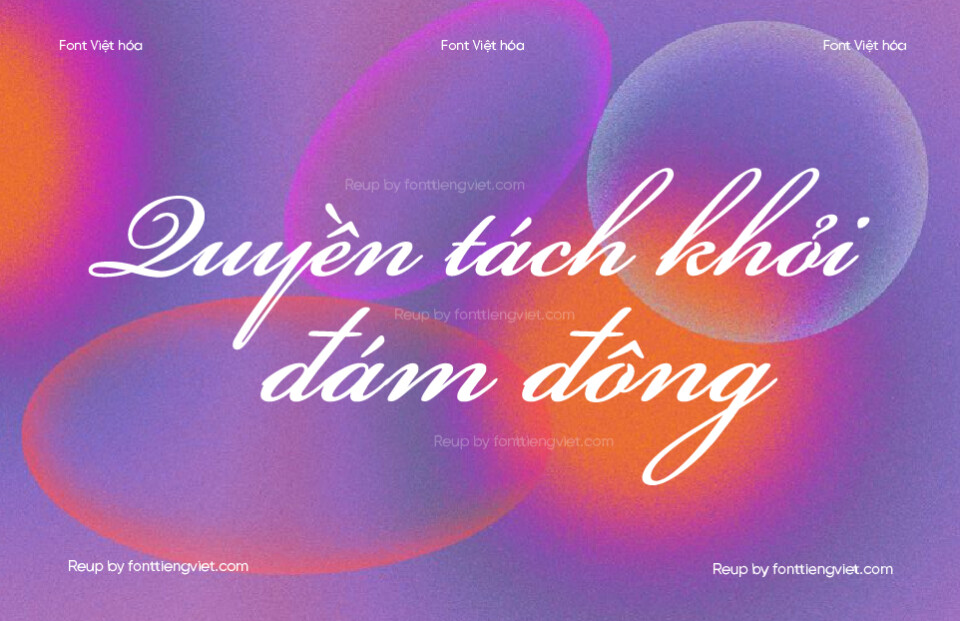
Trong thời đại số, việc trình bày tài liệu, luận văn hay các dự án học tập không chỉ dừng lại ở nội dung mà còn phải đảm bảo tính thẩm mỹ cao. Một trong những yếu tố quyết định sự chuyên nghiệp chính là lựa chọn Font Chữ phù hợp. Nếu bạn đang tìm kiếm một bộ font vừa đẹp mắt, vừa dễ đọc lại được Việt hóa hoàn chỉnh, thì Font Việt hóa UTM Beautiful KT chính là lựa chọn không thể bỏ qua. Đây là giải pháp lý tưởng giúp học sinh, sinh viên tạo ra những ấn phẩm ấn tượng, từ bài thuyết trình đến báo cáo khoa học, đặc biệt quan trọng trong mùa thi tốt nghiệp và nộp hồ sơ.
Đặc Điểm Nổi Bật Của Font Việt hóa UTM Beautiful KT
Font Việt hóa UTM Beautiful KT thuộc nhóm font chữ script hoặc semi-script, mang lại cảm giác mềm mại, thanh lịch nhưng vẫn giữ được sự rõ ràng cần thiết. Sự kết hợp giữa nét truyền thống và hơi hướng hiện đại giúp font này trở nên đa dụng. Đây không chỉ là một font chữ đẹp mà còn là công cụ nâng cao chất lượng thị giác cho mọi tài liệu.
Thiết Kế Tinh Tế Và Khả Năng Việt Hóa Toàn Diện
Điều làm nên giá trị của bộ font UTM nói chung và UTM Beautiful KT nói riêng chính là khả năng Việt hóa hoàn hảo. Mọi ký tự tiếng Việt, bao gồm dấu thanh, chữ cái có dấu (ă, â, ê, ô, ơ, ư, đ), đều được hiển thị chính xác, không bị lỗi font hay ngắt quãng như nhiều font nước ngoài khác. Điều này cực kỳ quan trọng đối với các bài luận văn, báo cáo dài yêu cầu tính đồng nhất cao về typography. Font chữ này đảm bảo rằng các dự án học đường của bạn sẽ luôn chuyên nghiệp và dễ dàng vượt qua các bước kiểm duyệt về hình thức.
Để đánh giá sự ưu việt của font này, chúng ta cần xem xét các điểm sau:
- Tính Thẩm Mỹ Cao: Phù hợp cho tiêu đề, trích dẫn nổi bật hoặc các thiết kế mang tính nghệ thuật như thiệp mời tốt nghiệp.
- Độ Dễ Đọc: Mặc dù mang phong cách đẹp mắt, font vẫn đảm bảo độ rõ ràng, không gây mỏi mắt khi đọc các đoạn văn bản ngắn.
Ứng Dụng Thực Tế Của Font UTM Beautiful KT Trong Môi Trường Giáo Dục
Đối với học sinh cấp 3 chuẩn bị cho kỳ thi tốt nghiệp và sinh viên đang làm luận án, việc lựa chọn font chữ có thể ảnh hưởng đến cách người đọc (giáo viên, hội đồng chấm thi) tiếp nhận thông tin. UTM Beautiful KT là một tài sản quý giá cho các mục đích sau:
- Trình Bày Luận Văn Tốt Nghiệp: Tạo điểm nhấn cho bìa, mục lục hoặc các phần giới thiệu quan trọng, thể hiện sự đầu tư nghiêm túc vào sản phẩm học thuật cuối khóa.
- Thiết Kế Slide Thuyết Trình: Giúp các tiêu đề slide trở nên sinh động, thu hút sự chú ý của người nghe mà vẫn giữ được vẻ trang trọng.
- Đồ Án Thiết Kế Đồ Họa Cơ Bản: Lý tưởng cho sinh viên các ngành liên quan đến nghệ thuật, truyền thông muốn tạo ra các poster, infographic hoặc brochure quảng bá dự án trường học.
Việc sử dụng một font chữ chuẩn mực và đẹp như thế này giúp nâng cao uy tín của người trình bày. Nó thể hiện rằng bạn quan tâm đến từng chi tiết nhỏ nhất trong bài làm của mình, điều mà các giáo viên chấm điểm luôn đánh giá cao.
Để tối ưu hóa khả năng đọc trong các tài liệu dài, lời khuyên là nên kết hợp Font Việt hóa UTM Beautiful KT với một font chữ thân thiện, rõ ràng khác (ví dụ: Times New Roman, Arial) cho phần nội dung chính, và chỉ sử dụng UTM Beautiful KT cho các tiêu đề, phụ đề hoặc các đoạn trích dẫn quan trọng cần sự nổi bật. Sự kết hợp thông minh này sẽ giúp tài liệu của bạn vừa chuyên nghiệp, vừa thu hút.
Đầu tư vào chất lượng trình bày, đặc biệt là typography, chính là đầu tư vào thành công của các dự án học tập. Các học sinh, sinh viên khi nộp bài thi hay đồ án có hình thức đẹp mắt, thống nhất thường nhận được sự đánh giá tích cực hơn về tổng thể. Đây là một chiến lược nhỏ nhưng hiệu quả mà nhiều người thành công đã áp dụng.
Tóm lại, Font Việt hóa UTM Beautiful KT là một lựa chọn tuyệt vời cho mọi nhu cầu thiết kế và trình bày tài liệu học thuật tại Việt Nam. Với khả năng Việt hóa hoàn chỉnh, thiết kế ấn tượng và tính ứng dụng cao, font chữ này chắc chắn sẽ làm tăng thêm giá trị cho các dự án của bạn. Đừng ngần ngại sử dụng bộ Font Chữ chất lượng này để đảm bảo rằng mọi ấn phẩm học đường của bạn luôn đạt đến tiêu chuẩn cao nhất về cả nội dung và hình thức. Hãy tải về và trải nghiệm ngay hôm nay để thấy sự khác biệt mà nó mang lại cho quá trình học tập và chuẩn bị thi cử của bạn.